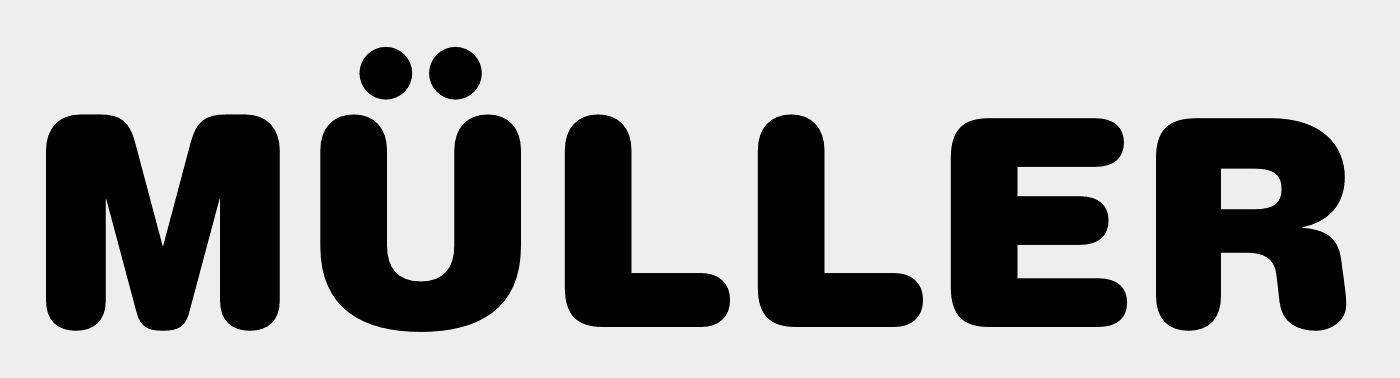
Schriftzug in Schuhhaus-Logo - welche Schriftart ist das?
Ich suche die Schrift, aus welcher der angehängte "MÜLLER" Schriftzug gefertigt wurde.
Da wurde sicher ein wenig gephotoshoppt, vermute ich, aber ich finde einfach die dahinter liegende Schrift nicht.
Die Helvetica Rounded Black kommt formal schon sehr nahe, ist allerdings etwas schmäler.